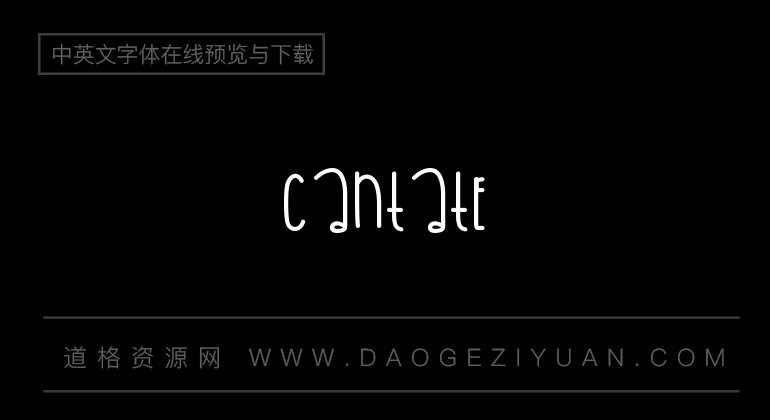
Cantate
Cantate 字体是一种英文字体,它具有优雅的外观和流畅的线条,适合用于标题和抬头。Cantate 字体的字母形状是深沉而优雅的,使用它可以让文字具有更强烈的视觉效果。Cantate 字体的线条细腻,它的字母形状也很精细,使用它可以使文字看起来更加精致。Cantate 字体的字母间距也很适中,使用它可以使文字看起来更加紧凑。
Cantate是一款非常不错的手写艺术字体,具有很好的视觉感,适合于文化类的宣传设计、商业类品牌的广告和产品包装设计以及个性化文字排版等较多场景。